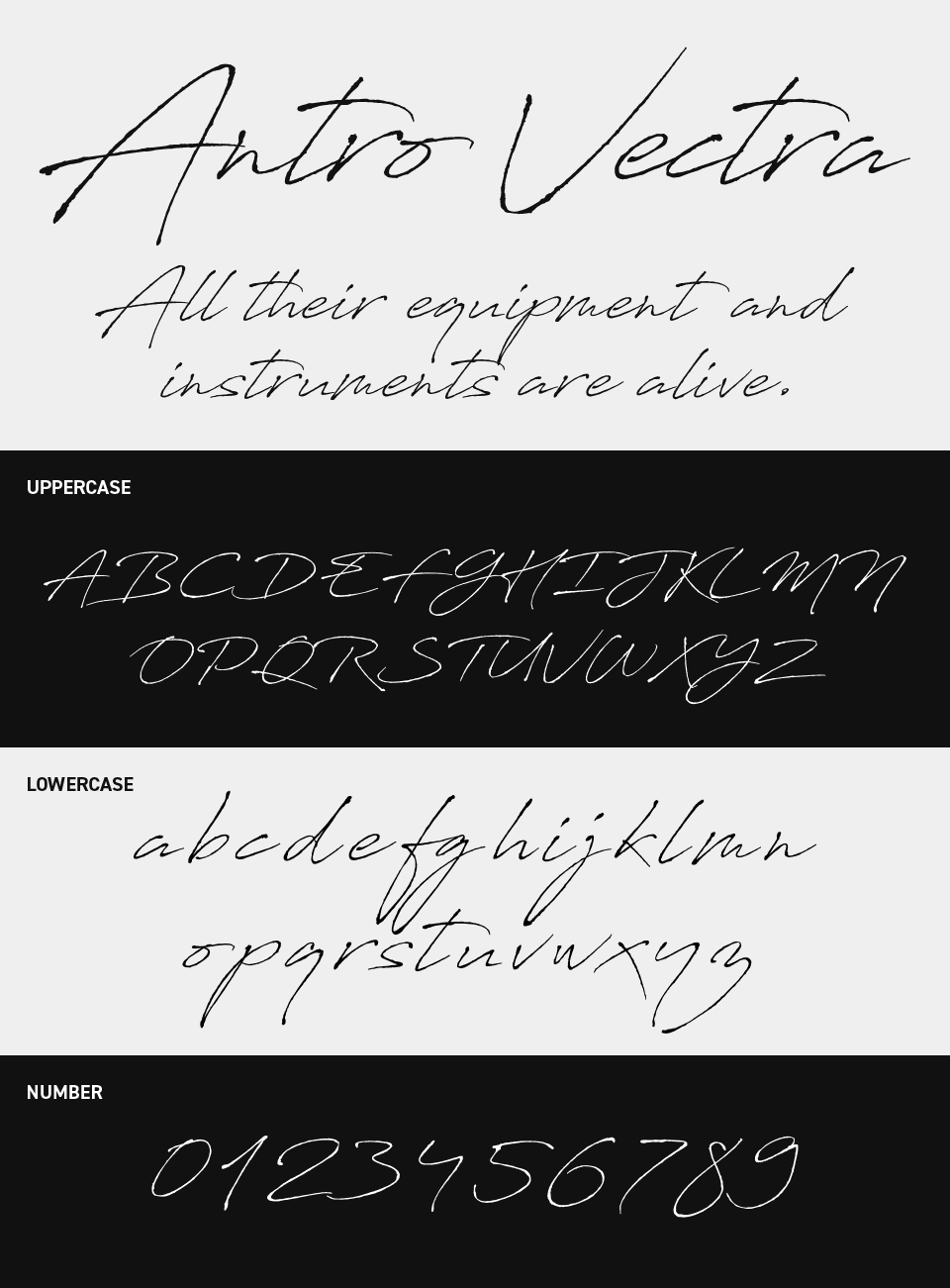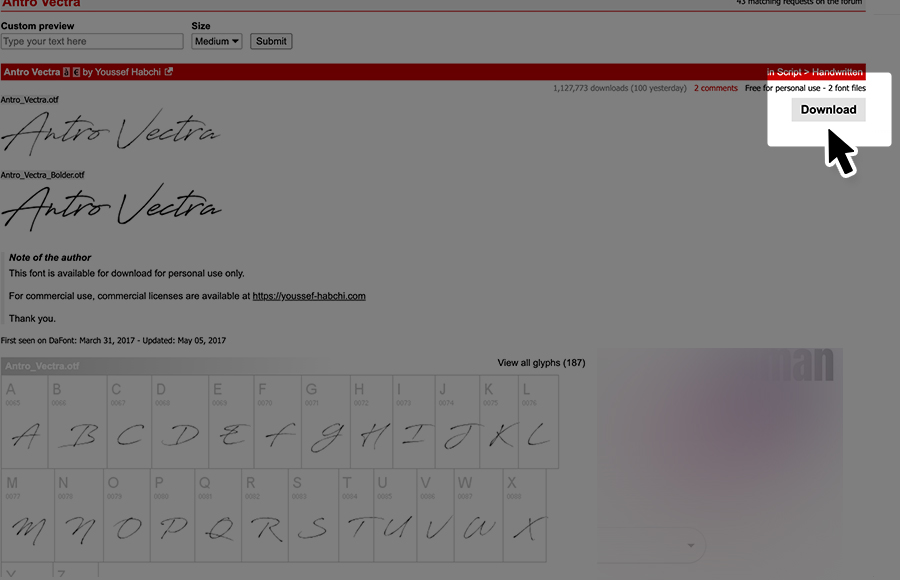
Antro Vectraフォントは、繊細なペンの筆致をそのまま写し取ったような、自由で伸びやかな手書きスクリプトフォントです。
細いストロークと自然なカーブが特徴で、まるで風に乗るように軽やかに文字が流れていく印象があります。大小文字を組み合わせたときに、リアルな手書き感のある味がでているとってもステキなフォントです。
どこか詩的でロマンチックな空気感があり、カードのメッセージやラブレター、日記のようなパーソナルな場面にぴったりです。少しクセのある線の跳ねや揺れが、無造作な美しさを生み、整いすぎない魅力があるフォントです。